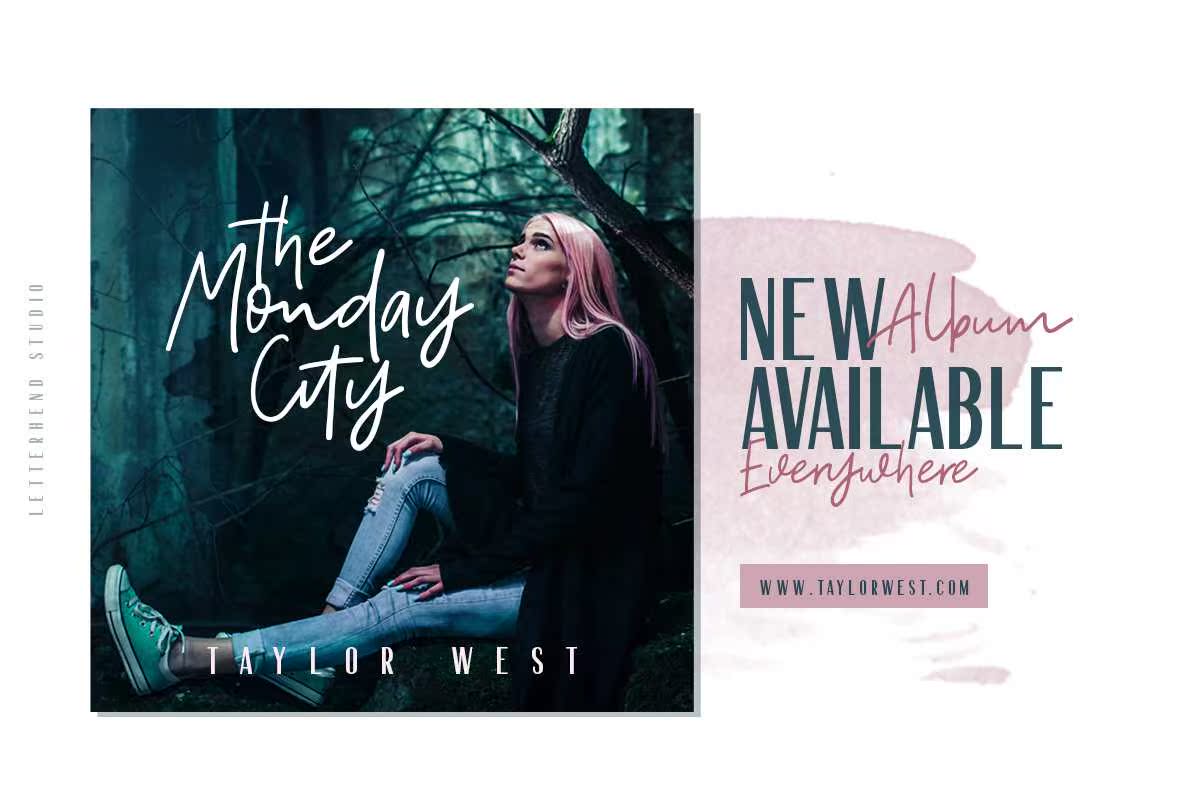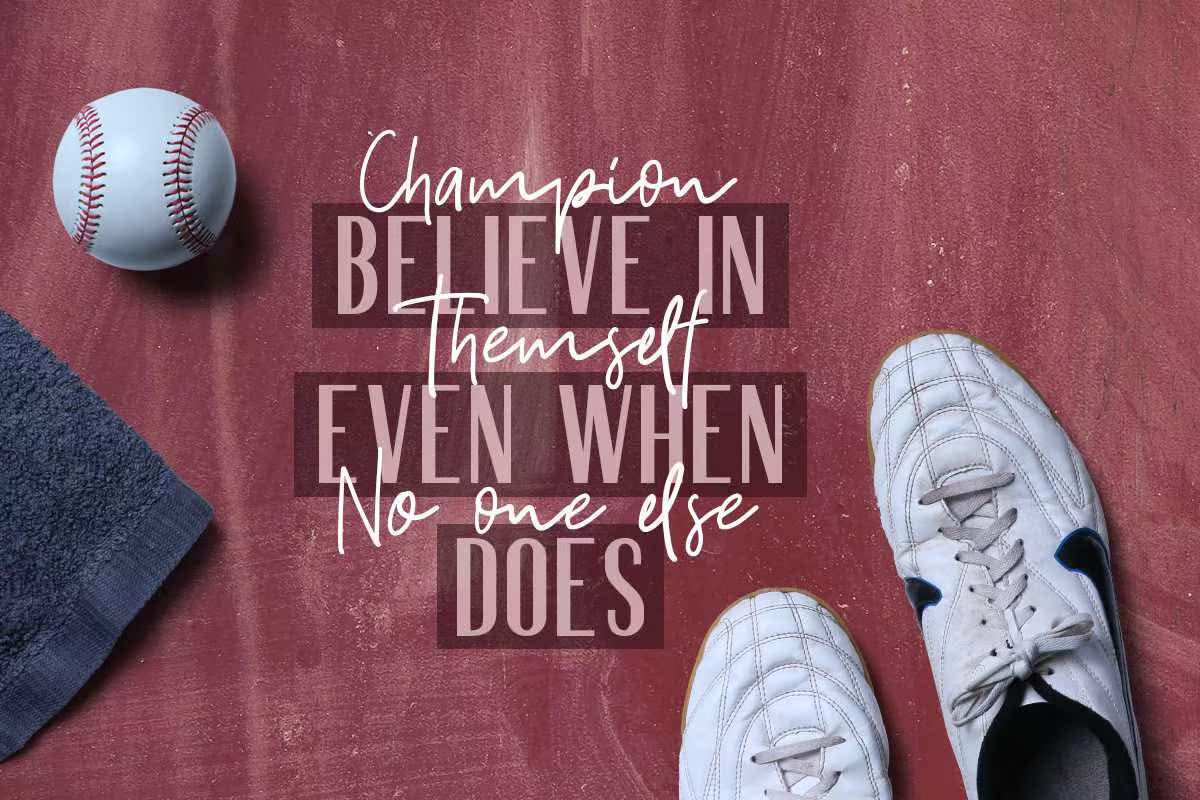
对于Collins而言,这是一个会带来ClassyEt偶然出现的时代。CondensedAnswers与自然手写脚本相结合,是您需要标题、标识、服装、邀请、品牌、包装、广告的完美匹配。此字体包括大写、小写、标点符号、符号和数字、文体设置、替换、连字、,ETCAL支持多语言。对于Collins,这是一种可以同时带来ClassyETCasualFeees的内容。CondensedSans与自然手写脚本相结合,是您需要标题、标识、服装、邀请、品牌、包装、广告的完美匹配。这种字体包括大写、小写、标点、符号和数字,文体设置交替、连字等支持多语言。